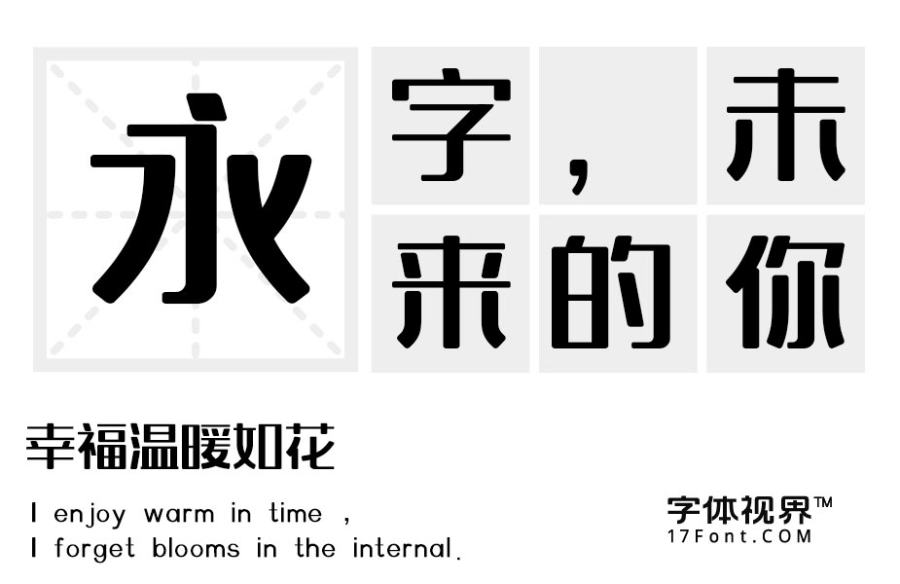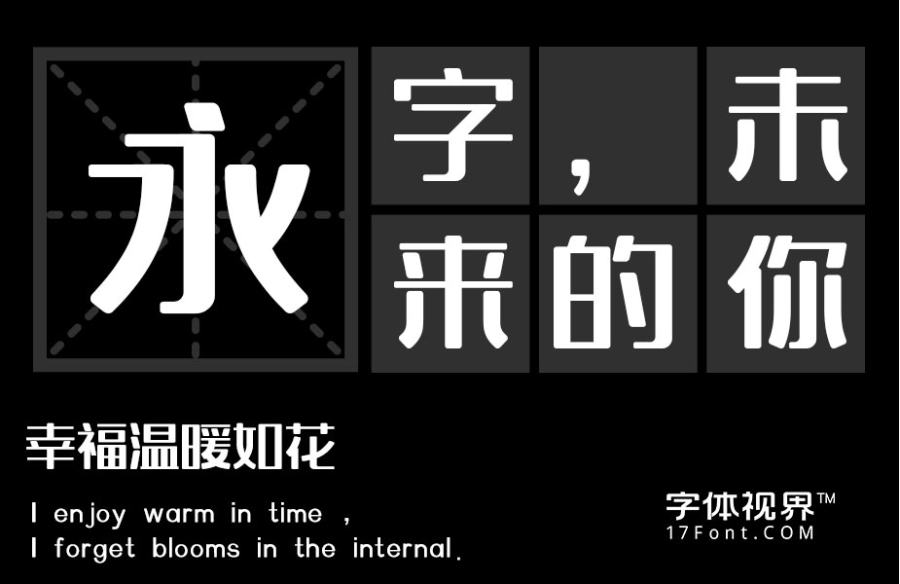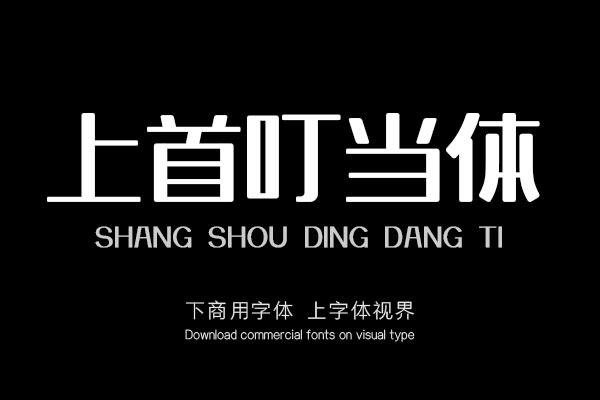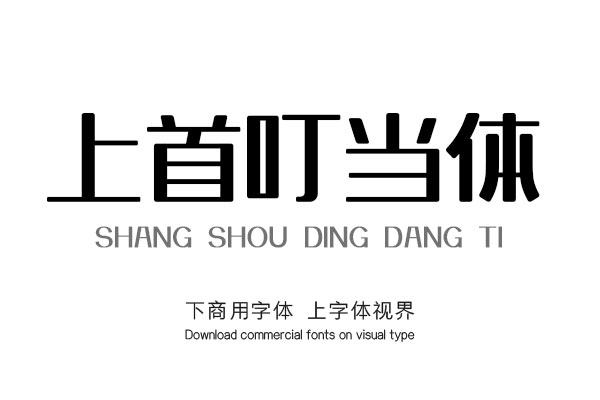
上首叮当体,字体风格方正,字体笔画竖勾、竖折都做了简化的处理。字库整体特征坚硬、有力,具有现代、国际化的指向性,适用于搭配标志、广告标语、商业广告等高端属性。购买须知:“下载服务费”与“字体VIP”所获得字体 仅用于个人非商用, 商用请联系付费授权。本字体为电脑用字,手机没有root权限不支持直接手机换字(手机如何root,请自行百度搜索教程)。购买前请先 了解清楚后再付款 ,字体为虚拟产品无法回收 一旦购买不支持退款。